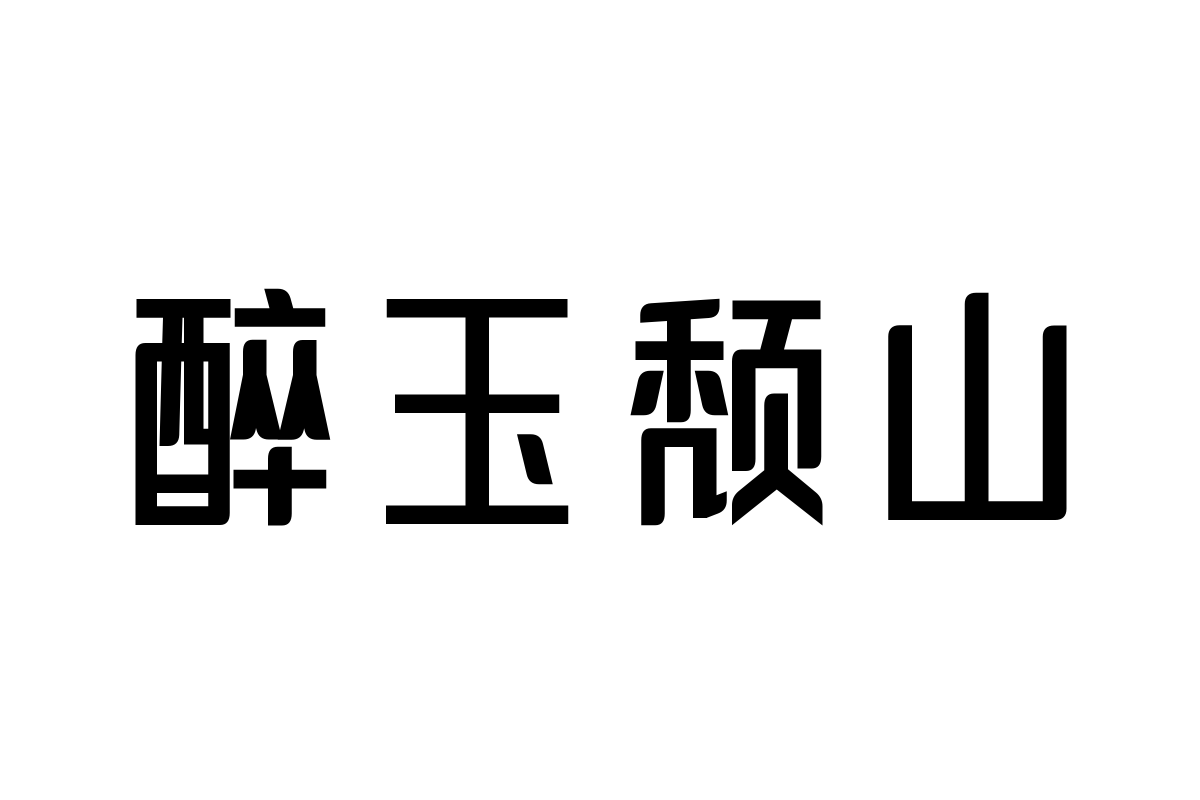
三极琼影简体是一款印刷字体,具有工整简洁的特点,并拥有强烈的视觉冲击力。它适用于报纸、杂志和书籍等场合,同时也适合海报、个性促进品牌标志设计及字体设计等环境使用。
三极琼影简体字体的整体结构灵活不呆板,笔画与字形的结合使得整体显得端庄高雅而不失风度。特别是点的设计,乍一看犹如微风缓缓吹拂着的柳叶,风度翩翩。这种独特的设计使得三极琼影简体在视觉上给人以美感,能够吸引人们的注意力。